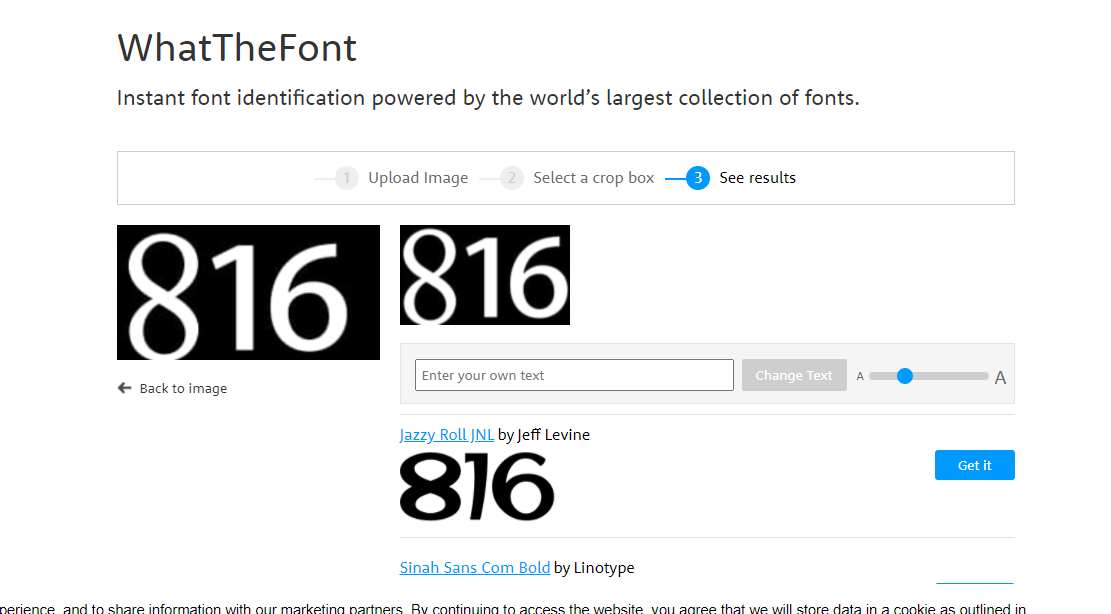
Arkadaşlar bu font nedir, elinde olan var mı yada nereden indirebilirim
deneyebilirsin daha farklı karakter varsa whatthefont com dan
8 times new roman olmalı, 1 ve 6 'nın fontu ise farklı hocam.
816 butiğin logosu sanırım bu.
fontla ilgili nasıl bir isteğiniz var çizebilirim isterseniz aynısını
8 serif bir font. 16 da sans bir font. Tahminen herhangi bir fontu kullansanız da bu sonucu alırsınız.